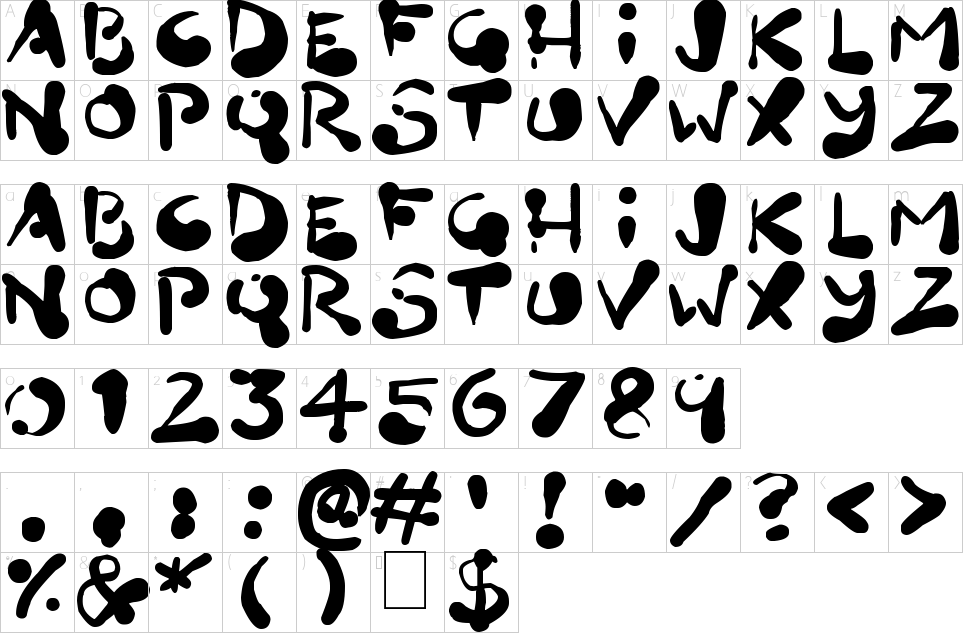
A fonte Paint Blobs é uma criação original de Darrell Flood, disponível gratuitamente tanto para Windows quanto para Mac. Suas letras desenhadas em forma de bolinhas criam um estilo lúdico e colorido que certamente enriquece o design de qualquer projeto. Com uma alta popularidade, Paint Blobs tem sido baixado mais de 3.186 vezes, o que sugere seu grande potencial para tornar seu design mais atraente e criativo. Esta fonte é um excelente recurso para quem busca uma maneira divertida e colorida de personalizar seus projetos, seja em tarefas manuais ou no design digital.